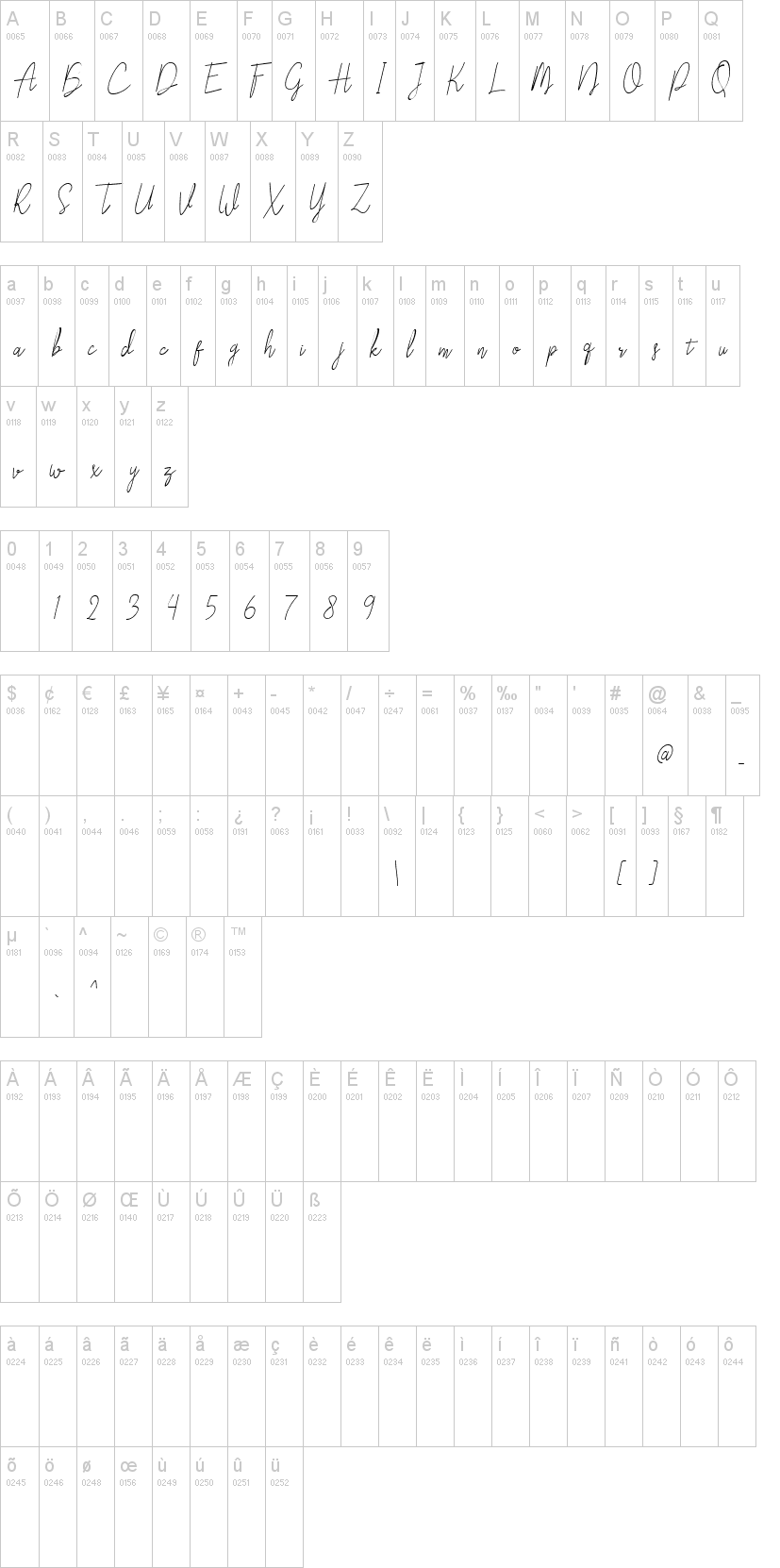
Liberika Oblique 是一种英文字体,其特点是具有斜体风格。它由字体设计师 Arkandis Digital Foundry 制作,于2017年首次发布。Liberika Oblique 字体的外观流畅,对比度适中,适合用于标题、标语、海报和其他需要强烈视觉冲击的设计作品。此外,该字体具有开放源代码许可证,可以免费下载和使用,这使得它成为广泛使用的字体之一。内容介绍
Liberika Oblique是一款非常不错的手写艺术字体,具有很好的视觉感,适合于文化类的宣传设计、商业类品牌的广告和产品包装设计以及个性化文字排版等较多场景。